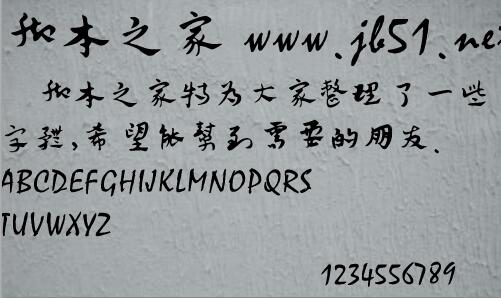
章草字体
章草字体是一款效果不错的手写中文字体,该字体笔触粗细适中,线条流畅自然,整体效果非常出众,具有强烈的视觉冲击力,可以应用于文本装潢、信息展示、网页设计、篆刻制模英文、数据制作、装潢设计、计算艺术设计、视觉设计、字帖等一切合法应用场景,也适应于报纸和杂志和书籍中常用字体,海报环境使用,有喜欢的朋友可免费下载收藏。